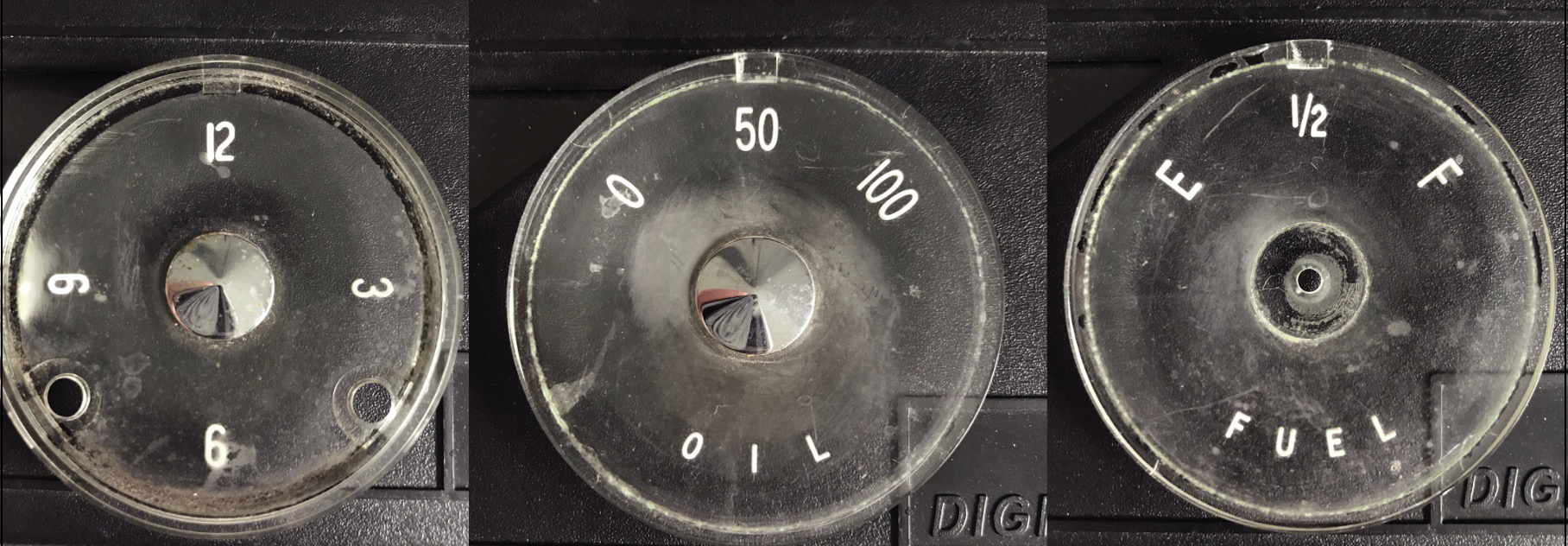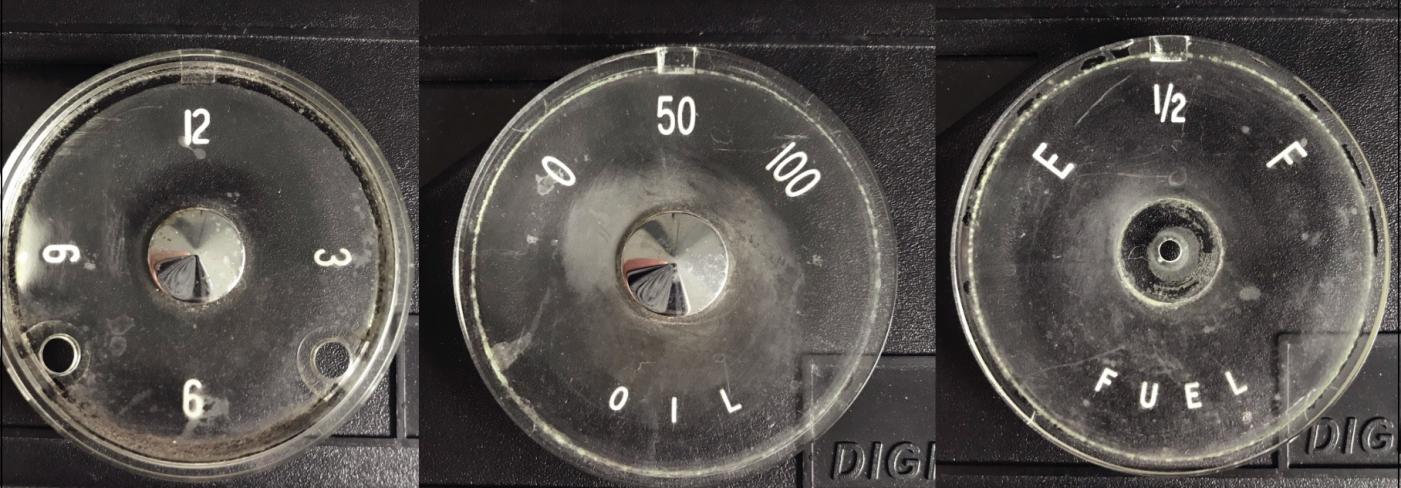
Schriftart Tachos eines Oldtimers (Volvo)
Hallo zusammen, ich suche eine Schrift die möglichst nah an die Tachos eines sehr alten Volvos rankommt.
Ja, ein paar Buchstaben und Ziffern aus einer Zeit, in der die Designer von solchen IUnstrumewnten diese Schriftzeichen noch von Hand gezeichnet haben, weil dies erheblich einfacher war, als soch erst einen Schriftsetzer zu suchen, der einen die paar Schriftzeichen in Blei setzte, und davon auf Papier einen Abdruck machte, den man dan doch von Hand nachzeichnen musste. Benannte digitale Schriften für solcjhe Zwecke gab es damals noch nicht.